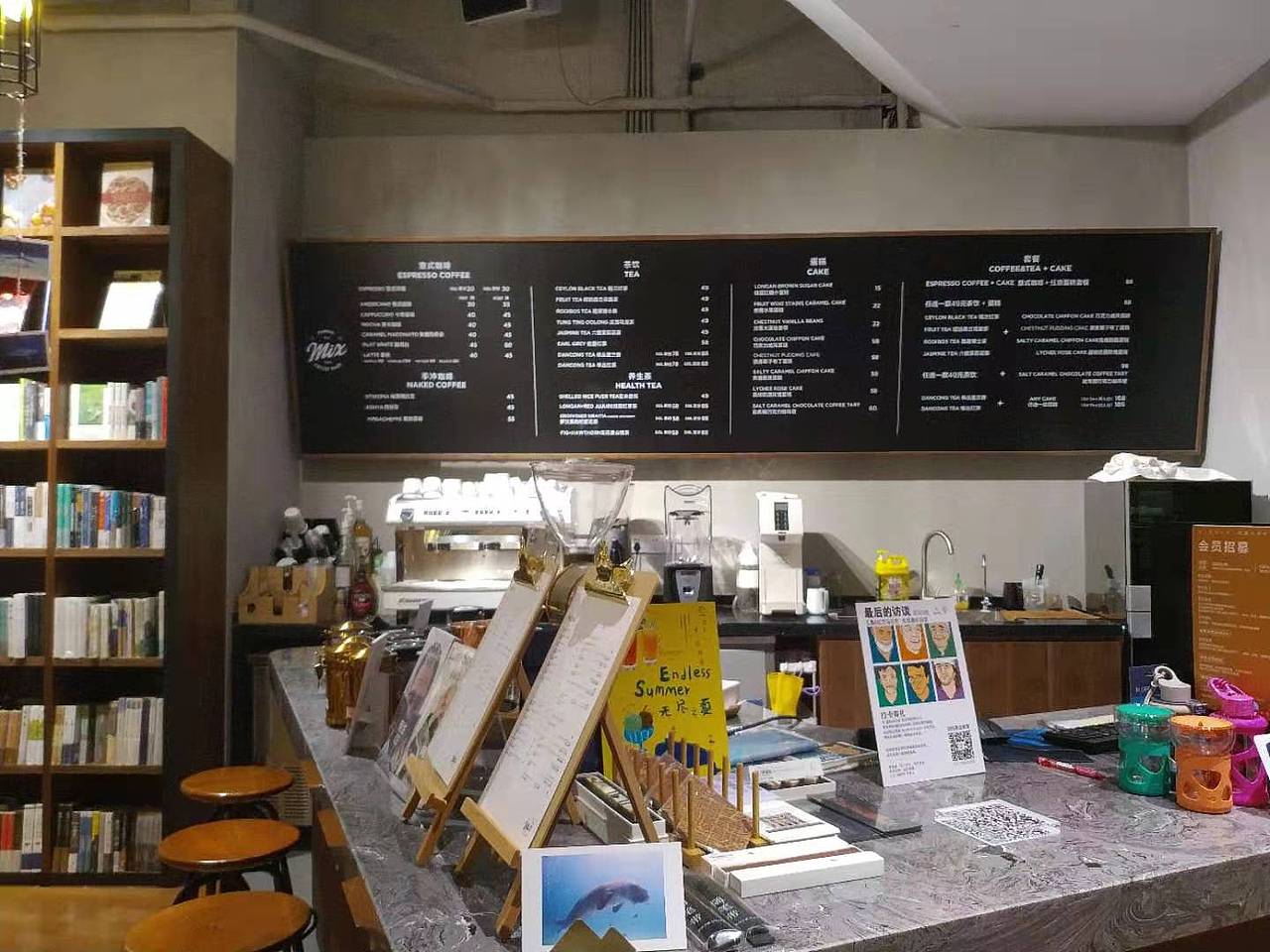
咖啡吧视觉平面设计
给书店的咖啡吧的分类视觉导视更新,主要是更新黑板菜单,目的是为了降低客人点单难度,提升点单率,以及每一季度的产品拍摄和海报设计。
这是更新前的黑板菜单,字体分级不明显,品项多,价格不突出等问题
黑板菜单更新后,把咖啡类,和茶饮类分为大类,加入照片,更加直观,套餐区加入手绘,图画视觉比文字更加让让容易理解
并且加上当季新品区